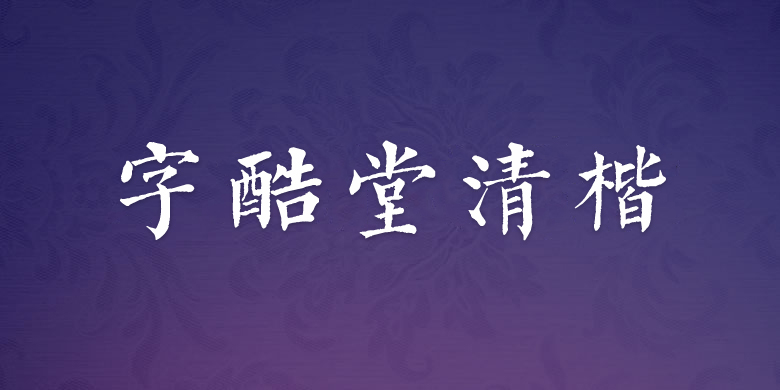
品牌:方正字库字酷堂设计师:过中运,王文娜发行时间:2017字库编码:简繁扩展(GBK)、大陆简体(GB2312-80)、繁U(GB12345-90-U)分类:常规书写·毛笔字体属性:精品字
该字体复刻自道光29年河北知府彭玉雯刊、书家梁绍鸿写刻上版的《十三经集字摹本》,是一套专为初学者准备的识字教材。该刻本刊刻较精,尤其是字样较大,收字又多,给当今复刻提供了较好的条件。